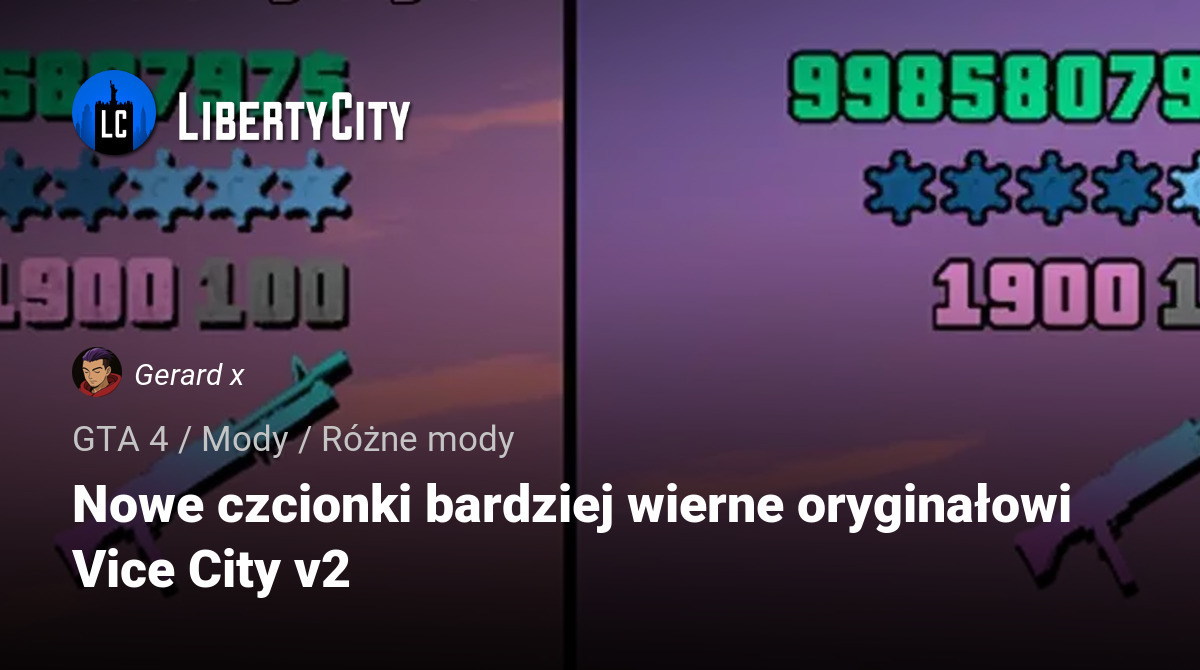
Nowe czcionki bardziej wierne oryginałowi Vice City v2
Druga wersja ulepszonej czcionki, która dokładniej oddaje styl oryginalnego GTA Vice City.
Co nowego:
- Dwa style wyświetlania pieniędzy i amunicji
- :Styl klasyczny — jak w poprzedniej wersji moda;
- Styl Definitive Edition — w stylu zaktualizowanego Vice City.
- Czcionka napisów z klasycznej wersji gry;
- Naprawione wcięcia między literami, poprawiona czytelność;
- Poprawne wyświetlanie nazw transportu i lokalizacji.
New fonts more faithful to the original Vice City v2
The second version of an improved font that more accurately captures the style of the original GTA Vice City.
What's New:
- Two styles of displaying money and ammo
- :Classic Style — as in the previous version of the mod;
- Definitive Edition Style — in the style of the updated Vice City.
- Subtitle font from the classic version of the game;
- Fixed indents between letters, improved readability;
- Correct display of transport and location names.